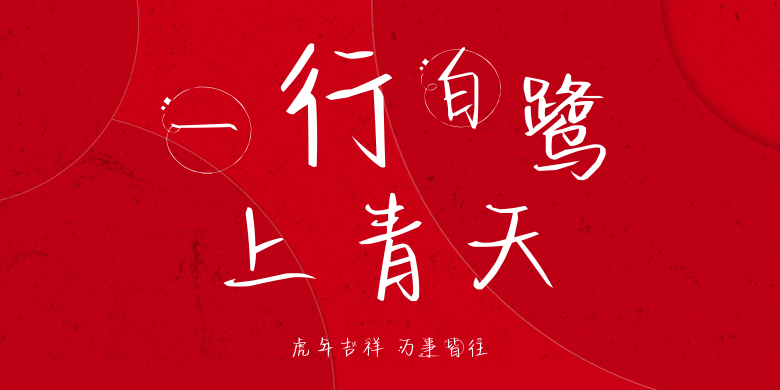
虎年吉祥 万事皆往,这款字体结构工整、笔画清晰,兼顾美观与易读性,适用于标题、正文、海报、包装、LOGO 等多种场景。字形优雅稳定,风格百搭耐看,适配日常排版与创意设计,让文字呈现更舒适、更具质感。虎年吉祥 万事皆往一笔一画,皆是细节,以均衡的比例、流畅的线条打造舒适视觉体验,字形端正大气,风格简约现代。无论是商业设计、品牌宣传还是日常排版,都能轻松驾驭,让文字更有格调与力量。虎年吉祥 万事皆往字体下载。